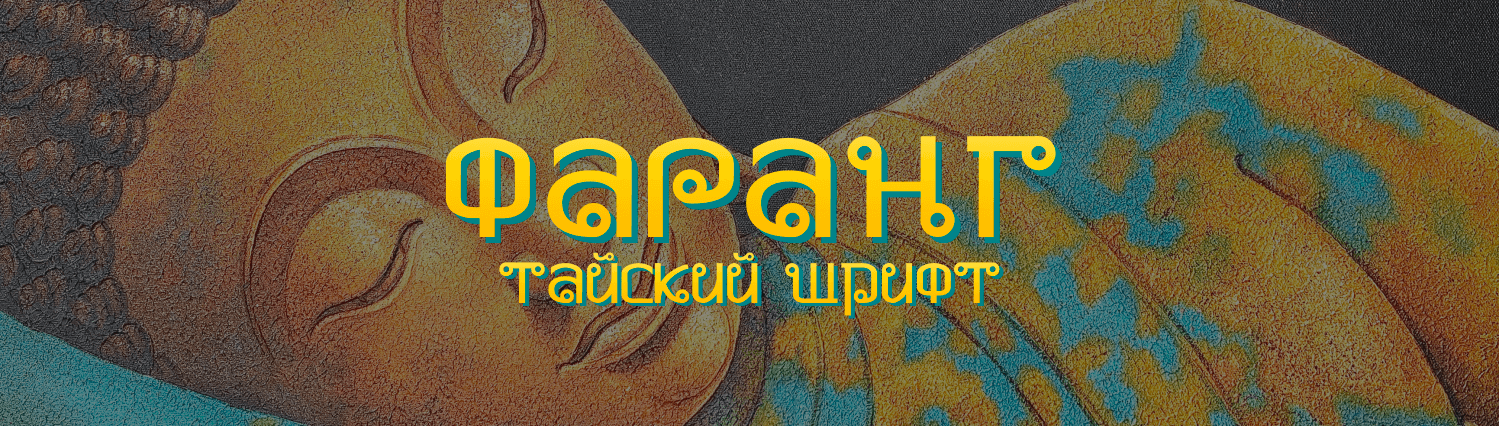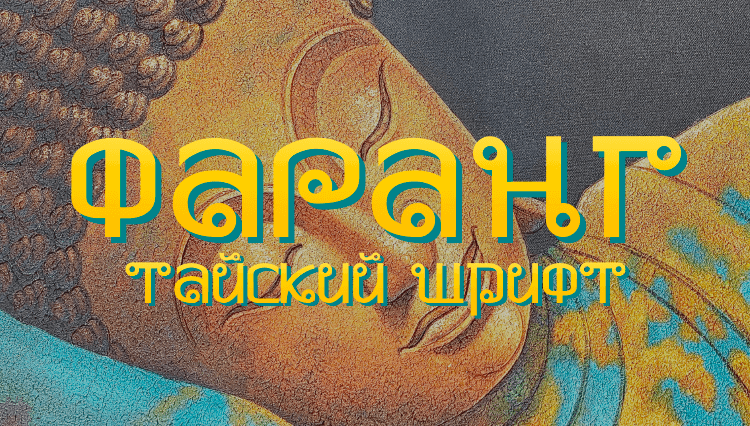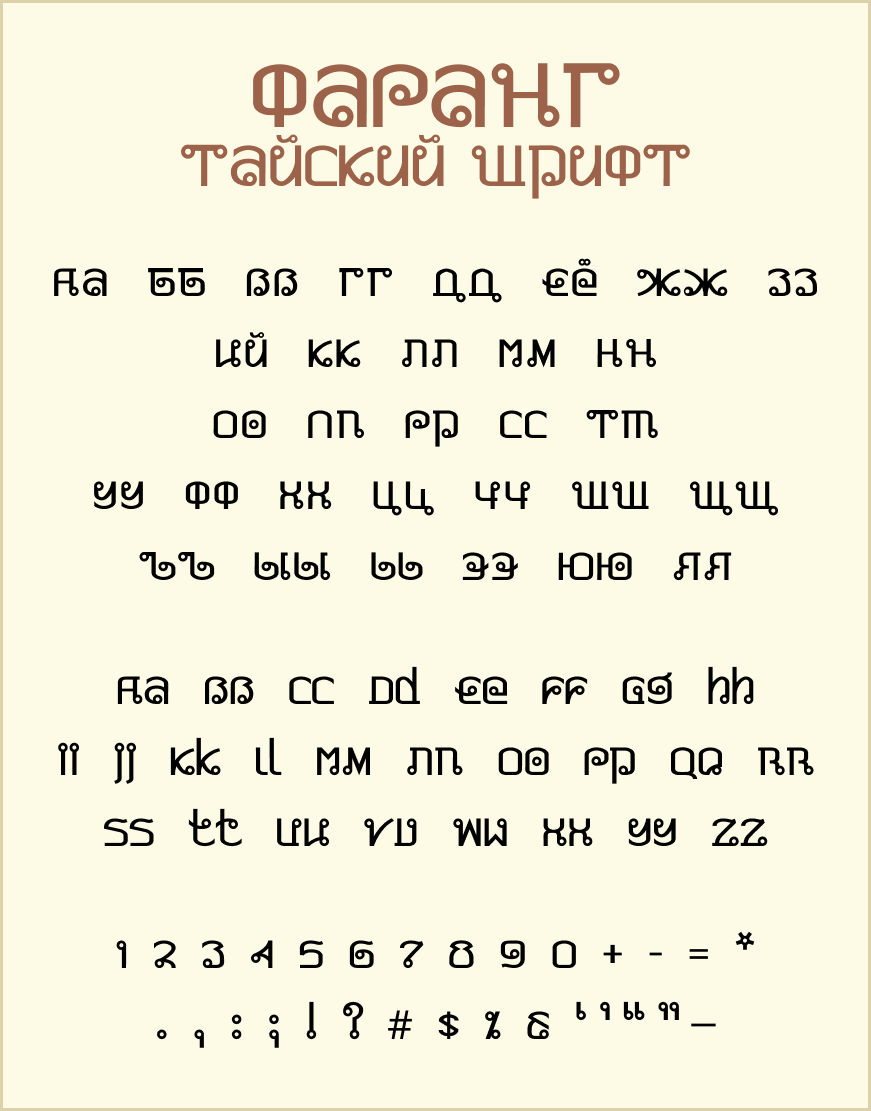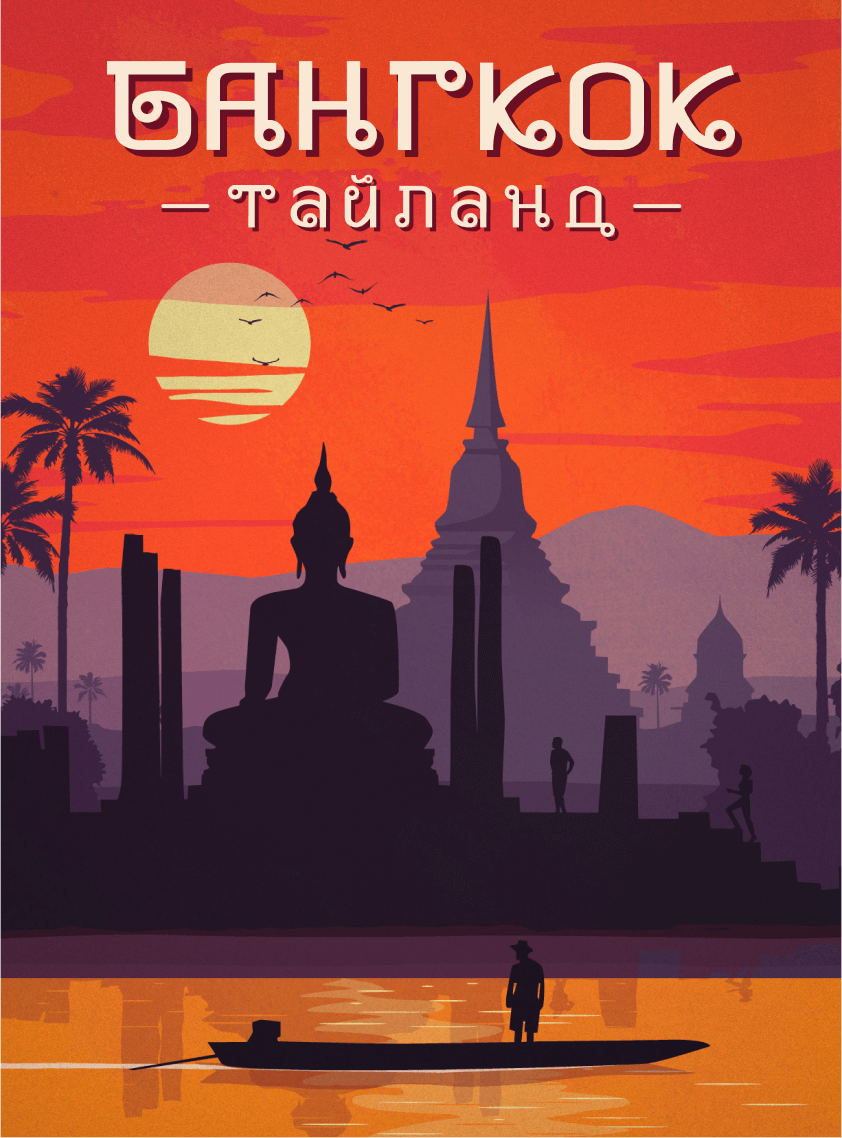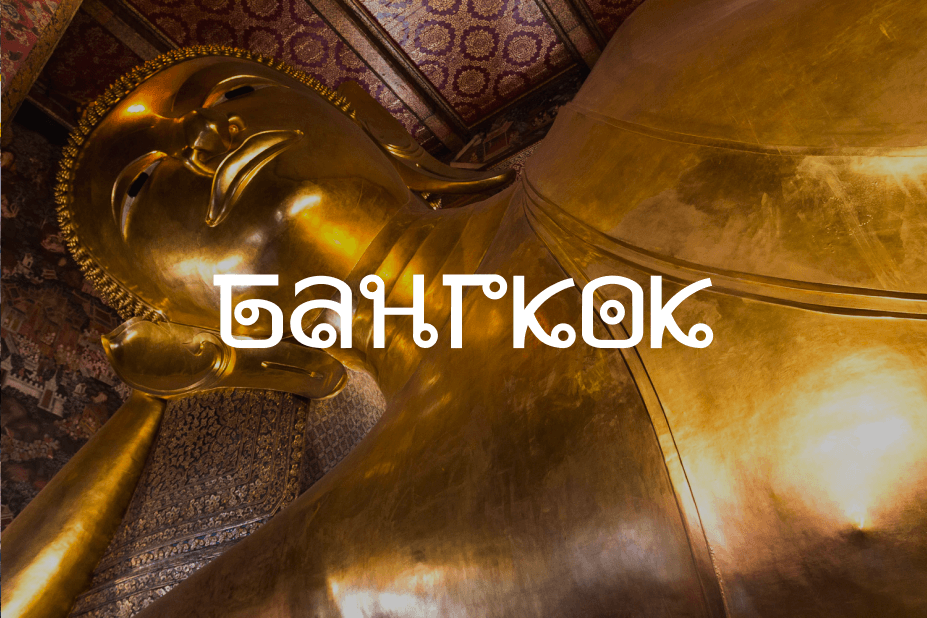
Шрифт в тайском стиле Фаранг
Фаранг — кириллический шрифт в стиле тайского письма. Фаранг создан на основе бесплатного шрифта Pad Thai, в который добавлены русские буквы.
Тайское письмо основано на сложном алфавите, в котором 44 согласных буквы, 15 огласовок и 4 тоновых маркера. Тайские буквы очень похожи друг на друга, не говоря уже о том, что слова при письме не отделяются пробелами. Все это делает тайский язык сложным для изучения.
Сами же буквы состоят из ломаных, вьющихся линий и кружков, свисающих с букв будто апельсины с ветки.
Дизайнер оригинального шрифта Pad Thai стилизовал латинский алфавит очень точно. Некоторые буквы похожи на тайские до смешения. Удивительно, что и тайский алфавит, оказалось, так легко стилизуется под латиницу. Буквы B, W, U — неотличимы от тайского оригинала.
Шрифт Фаранг так же точно стилизует кириллические символы. Шрифт хорошо передает дух Тайланда и может использоваться в декоративных целях для открыток, постеров, афиш и так далее.
Шрифтом Фаранг написаны все заголовки в рассказах про Тайланд, Лаос и Камбоджу. Все эти страны используют письмо, так или иначе связанное с тайским.